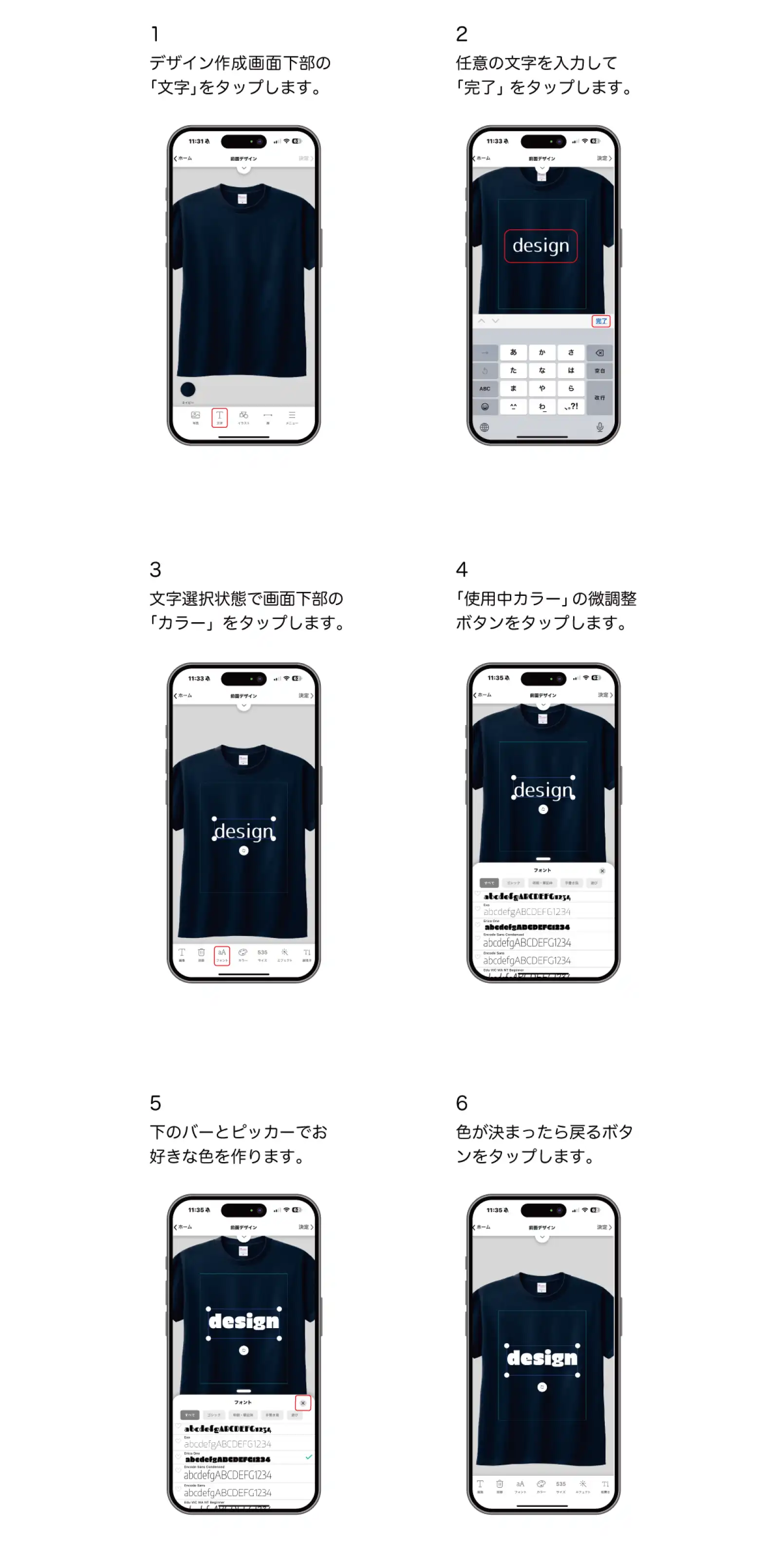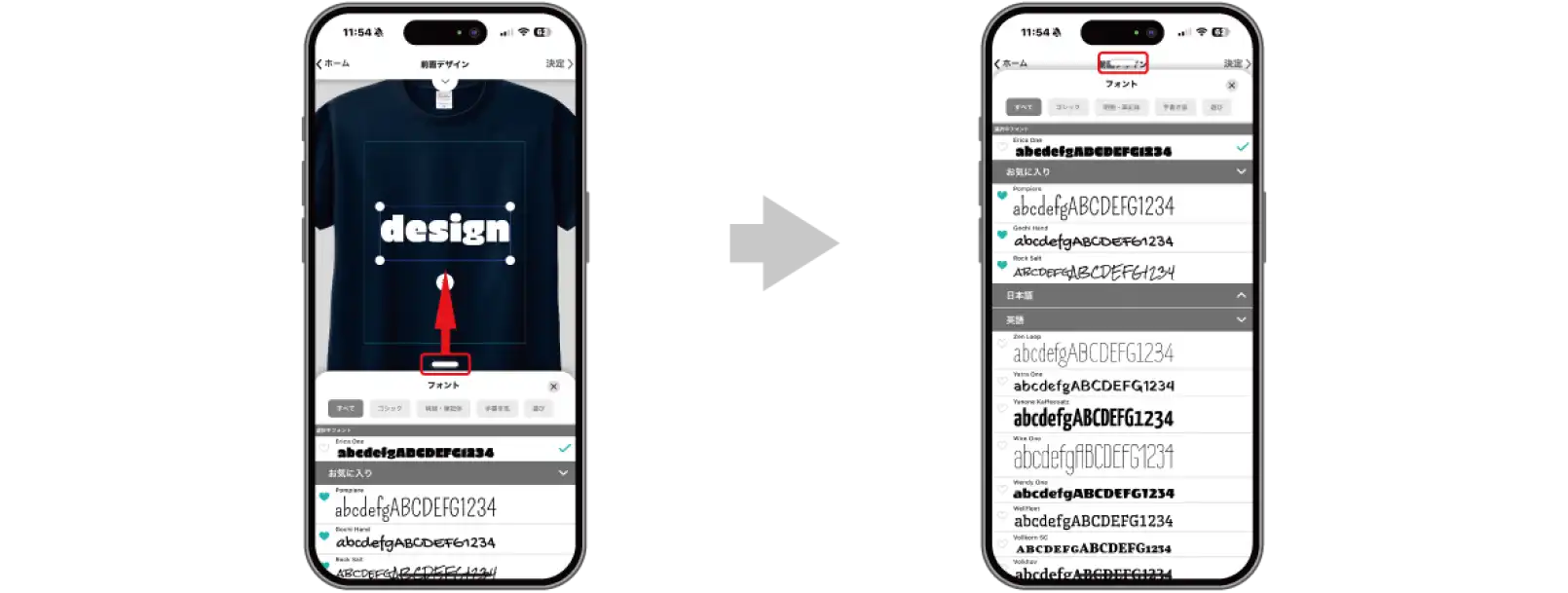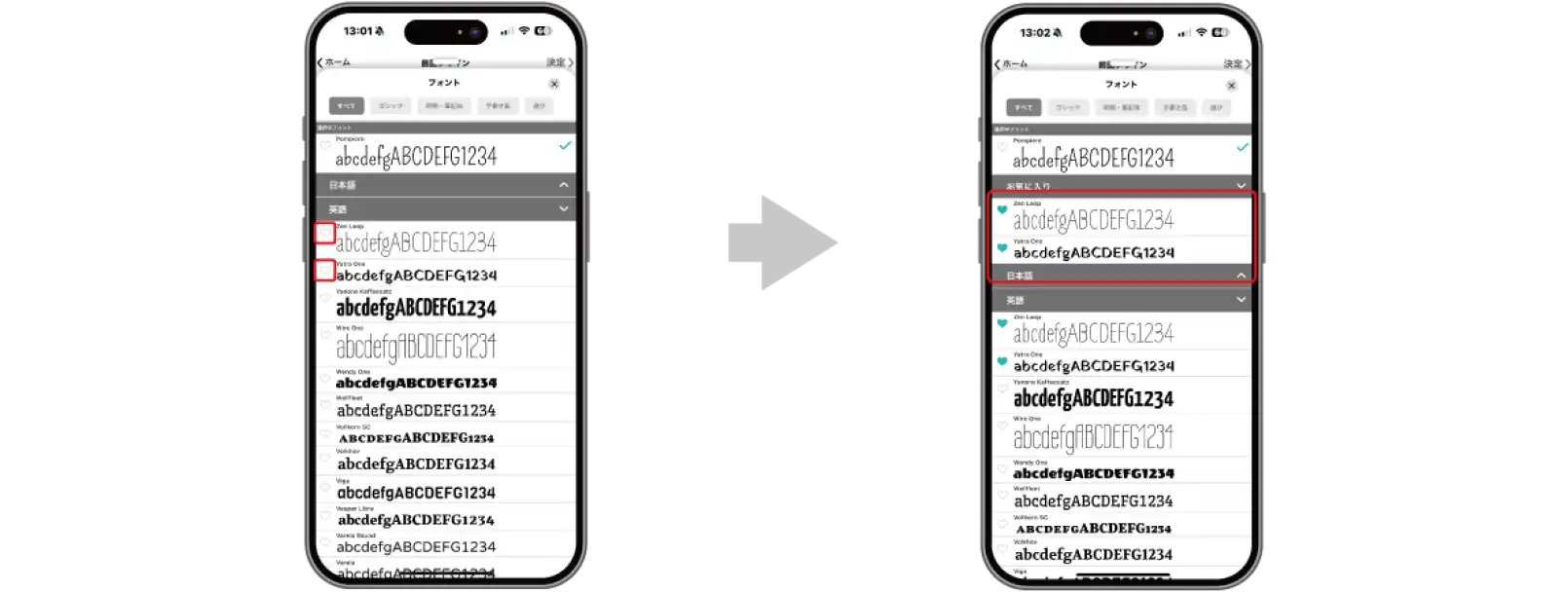
1. AirPriで文字のフォントを変える手順
デザイン全体のイメージに大切なフォントを変更する手順をご紹介します。
AirPriのアプリでフォントを変える手順
AirPriのアプリでフォントを変える手順はとてもカンタンです。デザインに文字をマッチさせるためには、フォントの変更は不可欠です。したにフォントを変える手順をご紹介します。
デザインを左右する文字のフォントを変える方法や、アプリ内で文字に対してできることをご紹介します。
デザインを作るときに、文字は情報を一番正確に伝えられるデザインオブジェクトです。ただ、他のデザイン要素(写真やイラスト)と文字のフォントが合わなければ、デザインの印象が全然違うものになってしまいます。文字のフォントは、デザインの良し悪しを左右する大きな要因です。 今回の記事では、文字のフォントに注目してお届けします。AirPriのアプリで文字のフォントを変更する方法や、ちょっとした裏技、文字に対してできることなどをご紹介します。
デザイン全体のイメージに大切なフォントを変更する手順をご紹介します。
AirPriのアプリでフォントを変える手順はとてもカンタンです。デザインに文字をマッチさせるためには、フォントの変更は不可欠です。したにフォントを変える手順をご紹介します。
フォントを探すのにちょっと役立つ機能をご紹介します。
フォントのメニューのように、下から出てくるメニューは上に伸ばすことができます。図のように、メニューの上にあるバーをもったまま、上にスライドすれば、フォントのメニューが縦にのびるので、画面が大きくなった分フォント選びも楽になります。
よく使うフォントや、好きなフォントは、お気に入りフォントとしてフォントメニュー内の上部にも表示させることができます。デザインの場面では、違うテキストボックスだけど同じフォントを使う場面がよくあります。そのたびにたくさんのフォントの中から同じフォントを探すのはとても面倒ですよね。フォントの左側にあるハートマークをタップしておけば、最大5つまでフォントをお気に入り登録しておくことができます。
AirPriは、機能がとても豊富です。それは文字に対しても例外ではありません。ここで、フォントの変更以外で文字に対してAirPriでできることもご紹介します。ここでは、AirPriで文字に対してできることをフォント変更の他に10個ご紹介しましょう。
入力した文字の色を変えることができます。単色だけでも300種類以上あるので、きっとあなたが望む色が見つかります。そのほかにも、色を細かく微調整できる機能もあります。詳しくは「AirPriのオシャレ機能!文字の色を変える!」でご紹介しています。
入力した文字の柄を変えることもできます。文字の中をグラデーションにしたり、パターンを入れたり、写真を入れることもできます。詳しくは下のリンクからどうぞ。
文字のサイズを変えることもできます。文字のサイズを変える方法は2つあります。離れた文字のサイズを全く同じサイズにしたいときなどにサイズの数値入力が役に立ちます。詳しくは「AirPriのデザイン機能!文字サイズを変更する」でご紹介しています。
文字のフォントを変えた状態でも、その文字にエフェクトをかけることができます。文字にエフェクトをかけると文字のデザイン性が一気に増します。詳しくは「AirPriのオシャレ機能!文字エフェクトをかける!」という記事でご紹介しています。
フォントを変えた文字もふち取ることができます。ふちの太さは直感的な操作でかえることができます。文字のふちの色もかえることができます。詳しくは「AirPriのデザイン機能!文字をふち取る方法」という記事でご紹介しています。
文字の透明度を変えることができます。ただ薄くするだけではなく、重なった部分の色が暗い色になる「乗算」や、重なった部分の色が明るい色になる「スクリーン」などもご用意しています。詳しくは「AirPriでデザインの透明度を調整する方法」という記事やインスタグラムの動画でもご紹介しています。
文字と文字の間を字間といいます。デザインの世界では字間の調整も不可欠です。例えば、写真の下にある文字が、写真の横の長さとピッタリ一緒だと綺麗なデザインに見えます。これを実現するのが字間調整です。詳しくは「AirPriのデザイン機能!文字の字間を調整する!」という記事でご紹介しています。 文章が数行あるデザインの場合、人が見て気持ちの良い行間があります。フォントによって、デフォルトの行間が決まっていますが、これを調整することも可能です。詳しくは「デザインに使う文字の行間を調整する方法」という記事でご紹介しています。
文字をわざと反転したオシャレなデザインもときどき見かけます。AirPriならもちろんそんなデザインもカンタンに作れます。文字の反転については「AirPriの助かる機能!反転機能を使ってみよう」という記事でご紹介しています。
今回はフォントの世界についてご紹介してきました。フォントの成り立ちは産業革命以前の活版印刷ですが、エジプト文明などの文字を含めればフォントの歴史はもっと古いので、人間とともに生きてきたフォントの歴史には感慨深いものがありますね。 フォントを知って、フォントを使えるようになればオリジナルデザイン作成がもっとたのしくなります。この記事が皆さんのデザインの一助になれば嬉しいです。